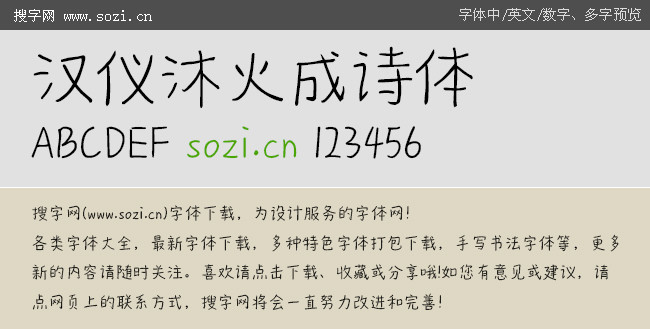
漢儀沐火成詩(shī)
搜字網(wǎng)給大家提供一款漢儀沐火成詩(shī)黑簡(jiǎn)體中文字體下載,漢儀沐火成詩(shī)是一款非常有趣的手寫字體。字體筆觸較為纖細(xì),書寫端正大氣。適用于兒童畫冊(cè)設(shè)計(jì)、卡通海報(bào)設(shè)計(jì)、包裝設(shè)計(jì)等場(chǎng)合使用。(本字體為個(gè)人非商用版,如需要商用請(qǐng)聯(lián)系漢儀公司購(gòu)買版權(quán))